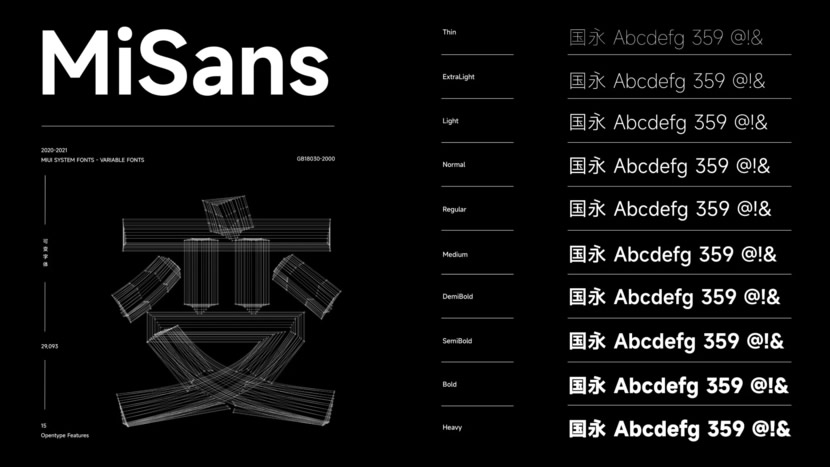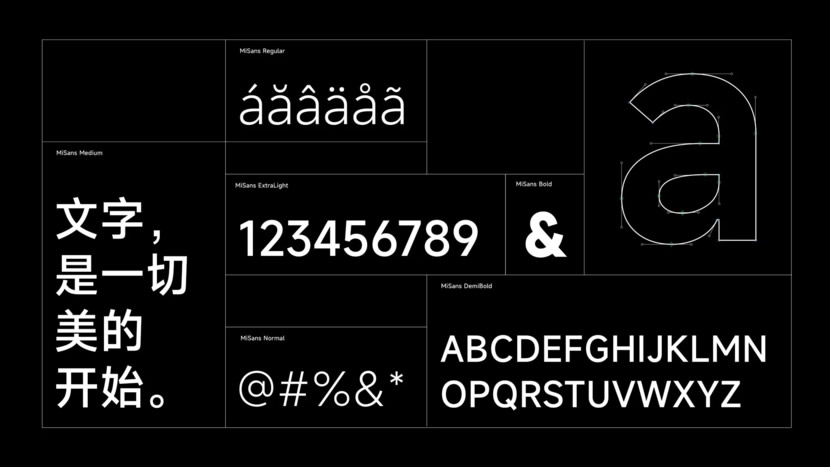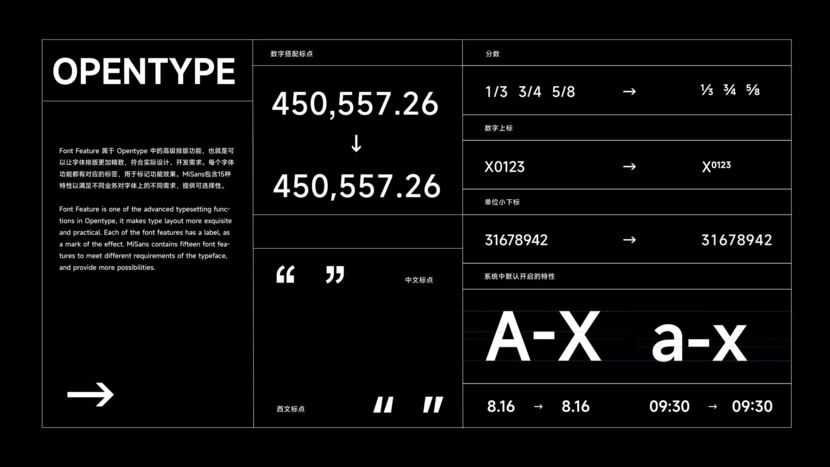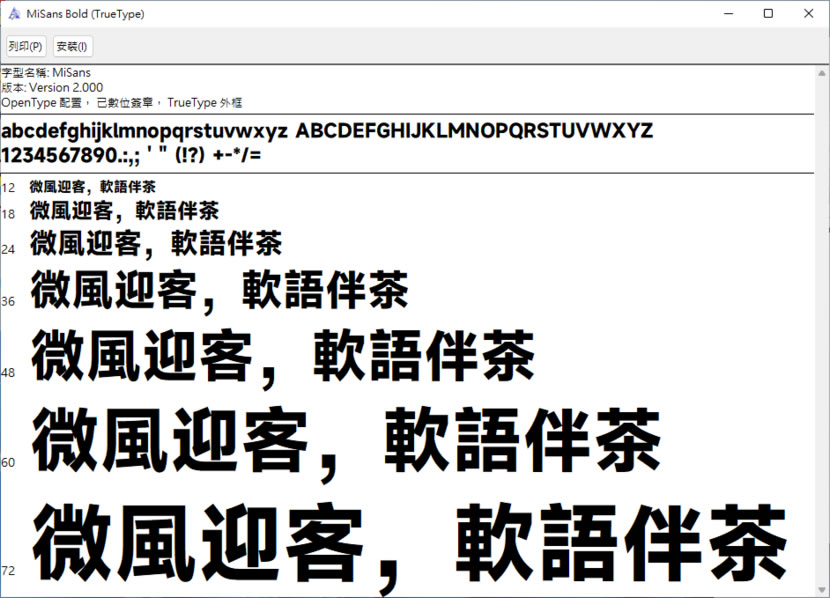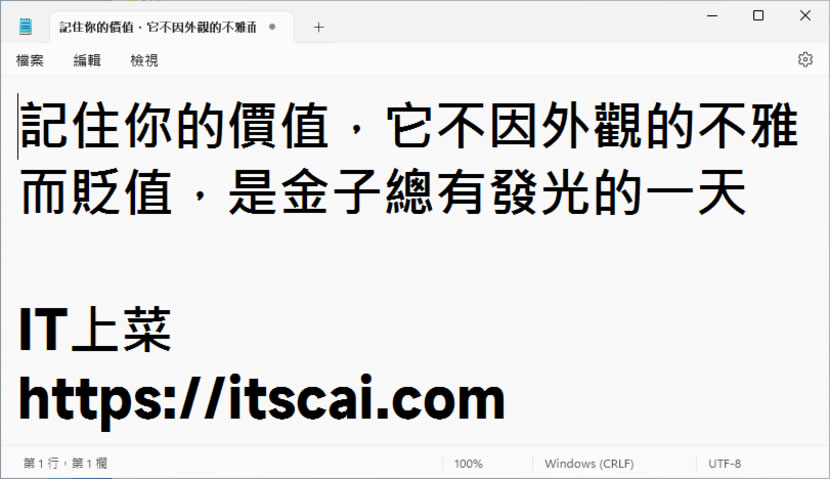
小米 MiSans 免費中文字型 10種字重支援繁體可商業用途
MIUI 是小米基於 Android 系統二次開發的作業系統韌體,並用於旗下小米手機、Redmi 手機、POCO 手機以及小米平板電腦的預裝作業系統韌體。這款作業系統所使用的字體稱為「MiSans」,是由小米自家開發的字型。現在,MiSans 字型已經釋出並開放給所有人免費下載!MiSans 字型的特點在於其筆畫更加筆直有力,看起來也更為簡約,減少了視覺疲勞,非常適合在行動裝置的小螢幕上使用。
根據說明,MiSans 字型共收錄了29,093個字元,並支援多國語言,包含繁體中文字體。MiSans 字型的特色之一是提供多種 OpenType 功能,可以根據特定需求選擇不同型態的字元,例如某些標點符號會根據周圍字母的型態自動調整到適合的位置。想要下載 MiSans 字型,只需前往「小米社區」頁面,找到 MiSans 字體的下載鏈結,即可順利獲得完整套的 MiSans 字型。這套字型包含十種字重,層次清晰,並且開放給所有人免費使用,同時也適用於商業用途而不受任何限制。
5.實際應用。